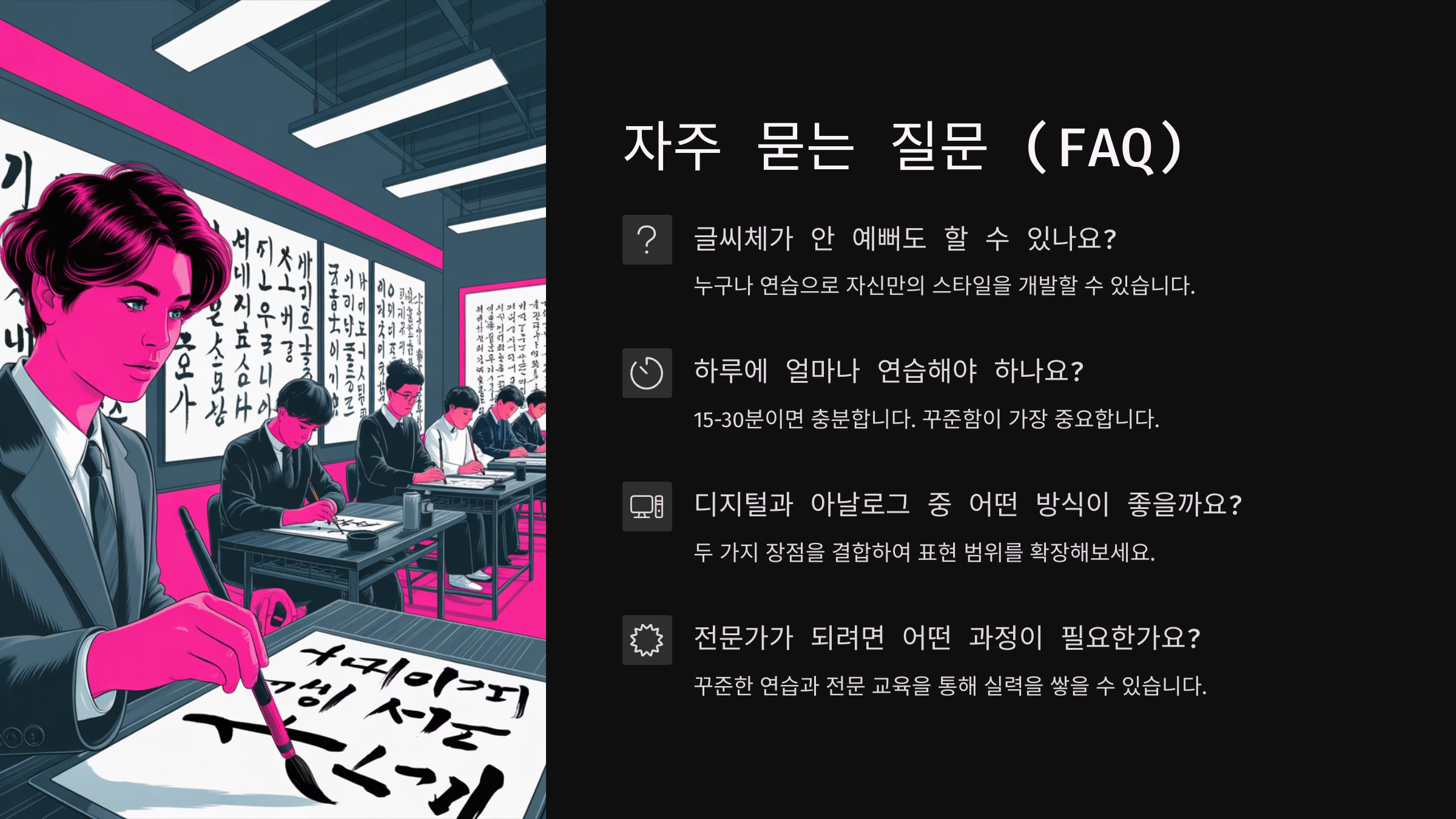
요즘 캘리그라피, 특히 감성글씨가 인기 많죠? 손글씨 특유의 따뜻함과 감성이 담긴 글자 하나가 보는 사람 마음을 울리기도 해요. 이 감성글씨는 단순한 디자인이 아니라, 글씨에 담긴 감정과 메시지를 전하는 예술 형태랍니다.
디지털 시대임에도 불구하고 사람들은 여전히 손으로 쓴 글씨에서 위로와 여유를 느끼고 있어요. 특히 SNS에서는 감성 캘리그라피 글귀가 수많은 공감을 얻으며 공유되고 있죠. '나도 저렇게 써보고 싶다'는 생각, 한 번쯤 해본 적 있지 않으신가요?
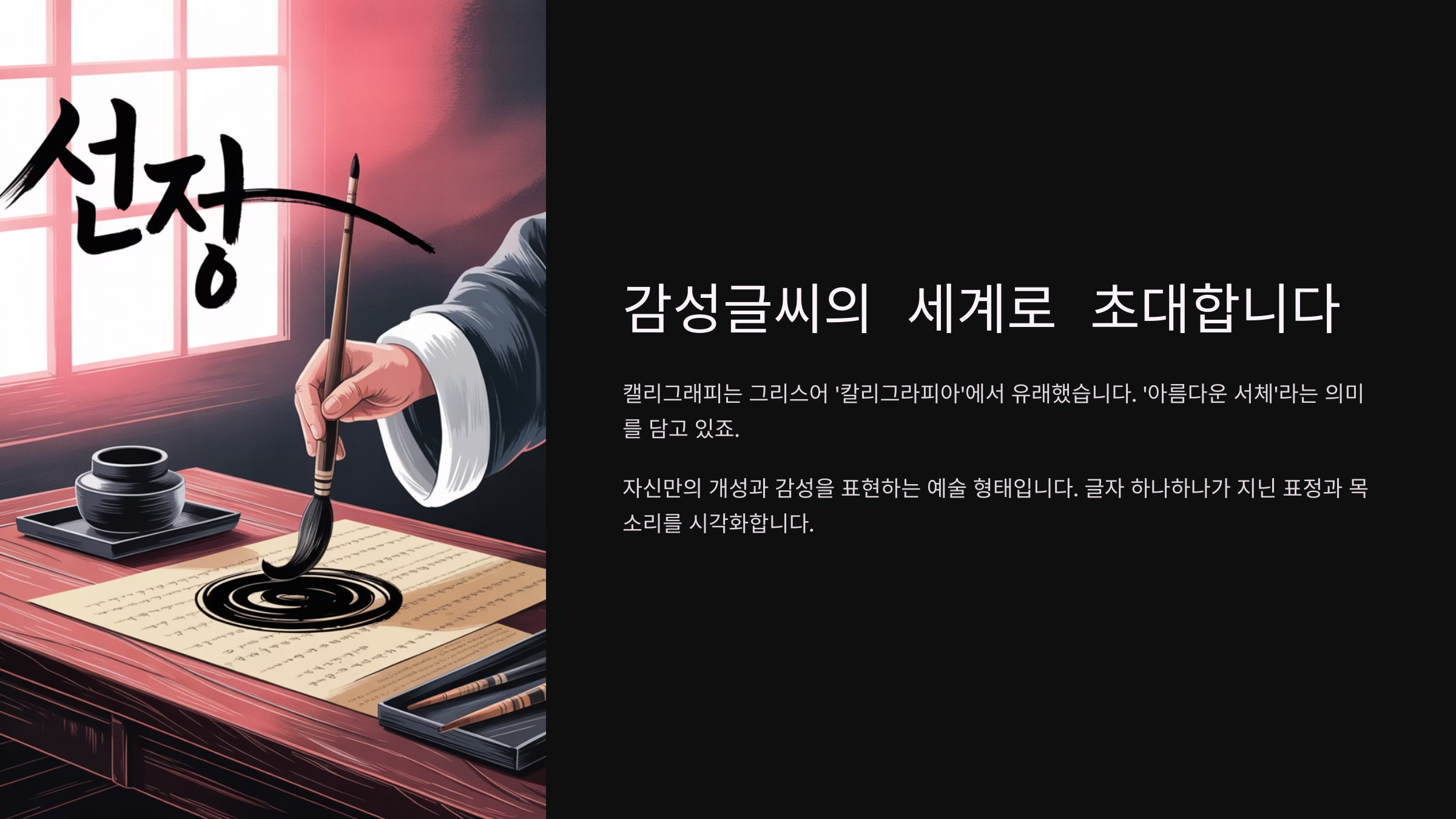
이제부터 그 질문에 대한 답을 찾아가볼게요. '나도 작가가 될 수 있을까?'에 대해 진심 어린 가이드와 함께 시작해보자고요 😊
✒ 감성글씨의 탄생과 유래
감성글씨의 탄생과 유래
감성글씨는 단순한 손글씨를 넘어서 하나의 감정 표현 수단으로 자리 잡았어요. 이 표현은 2000년대 후반부터 본격적으로 사용되기 시작했고, 특히 한국에서는 ‘글씨로 마음을 전하다’라는 문화와 연결되면서 큰 인기를 얻었죠. 붓펜과 만년필, 심지어 수성펜까지 활용해 개성 있는 글자체를 만들어내는 것이 특징이에요.글씨 하나하나에 따뜻한 감성과 이야기를 담는 이 작업은, 디지털 글꼴로는 느낄 수 없는 정서를 전달해요. 옛날 서예가 한문을 통해 뜻을 표현했다면, 오늘날 감성글씨는 일상 언어와 문장을 통해 감정까지 전하는 거죠.
예전에는 정형화된 글씨가 '예쁜 글씨'로 여겨졌지만, 요즘은 비뚤거나 흐트러져 있어도 괜찮아요. 오히려 그 안에서 더 인간적인 매력을 느낄 수 있으니까요. 손글씨를 통해 나만의 스타일을 표현하는 시대가 온 거예요.
이 감성 캘리그라피는 시인, 작가뿐 아니라 일반 사람들도 자신의 이야기를 담는 데 활용해요. 축하카드나 명함, 책갈피, 포스터 등에도 자주 쓰이고 있고, 온라인 클래스나 유튜브를 통해 배울 수 있는 콘텐츠도 무척 많아졌죠.
🖋 캘리그라피 장르별 특징 비교
장르 도구 특징 활용 예시 전통 서예 붓, 먹 획 중심, 격식 있음 한자, 명언 쓰기 현대 캘리그라피 붓펜, 사인펜 자유로운 선, 감성 강조 SNS글귀, 상품 포장 디지털 캘리 아이패드, 스타일러스펜 레이어 작업, 수정 용이 굿즈, 웹 포스터 캘리그라피는 이렇게 다양한 장르로 나뉘어요. 도구나 스타일에 따라 분위기도 달라지고, 쓰임새도 확연히 달라지는 게 참 흥미로워요. 내가 생각했을 때 감성글씨는 나만의 감정을 솔직하게 담아내는 하나의 언어라고 느껴져요 🧡
💗 왜 감성글씨에 끌릴까?
왜 감성글씨에 끌릴까? 사람들은 왜 디지털 폰트보다 감성글씨에 더 감동할까요? 이유는 바로 '사람의 손'이 느껴지기 때문이에요. 캘리그라피는 글자의 모양을 넘어 그 속에 담긴 감정과 분위기를 함께 전달해줘요. 그래서 그 한 줄이 누군가에겐 위로가 되고, 하루를 웃게 만들어주는 힘을 지니는 거죠.
특히 현대인들은 하루 종일 스마트폰이나 컴퓨터 앞에 앉아 있는 경우가 많잖아요. 그래서 종이에 손으로 쓰는 행위 자체가 힐링처럼 느껴지는 거예요. 글씨 하나에 감정과 정성이 담긴다는 걸 알게 되면, 그 매력에서 빠져나오기 힘들어요.
감성글씨는 '꾸며야 예쁘다'는 강박에서 벗어나 있어요. 삐뚤빼뚤해도 좋고, 조금 서툴러도 돼요. 중요한 건 그 글자에 담긴 마음이죠. 그 점이 많은 사람에게 편안함을 주고, 자신도 해보고 싶다는 욕구를 자극해요.
실제로 SNS를 보면 “오늘 하루 수고했어”, “있는 그대로도 괜찮아” 같은 짧은 문장이 손글씨로 적혀 있을 때 훨씬 더 와닿는 걸 볼 수 있어요. 폰트로 쓴 말보다 손글씨 한 줄이 위로가 되는 이유, 이제 아시겠죠? 😊
💞 감성글귀 반응 비교
문장 유형 글자 형태 느껴지는 감정 공감도 "오늘도 수고했어요" 폰트 텍스트 무난, 일상적 ★★☆☆☆ "오늘도 수고했어요" 손글씨 캘리 따뜻함, 위로 ★★★★★ 위의 비교처럼 같은 문장이라도 감성글씨로 표현되면 그 감동은 두 배 이상 커져요. 글씨체 하나로 누군가의 하루를 따뜻하게 만들어줄 수 있다니, 참 멋지지 않나요? 🎨
🖌 캘리그라피, 어떻게 시작할까?
캘리그라피, 어떻게 시작할까
감성글씨, 캘리그라피를 시작하고 싶다면 먼저 마음가짐부터 달라져야 해요. 완벽하게 써야 한다는 부담은 잠시 접어두고, ‘내 감정을 글씨로 표현한다’는 생각으로 시작해보세요. 처음에는 어색하고 마음에 들지 않아도 괜찮아요. 꾸준히 쓰다 보면 글씨에 나만의 분위기가 자연스럽게 묻어나거든요.가장 먼저 해야 할 일은 다양한 캘리그라피 스타일을 관찰하는 거예요. SNS나 유튜브에서 ‘캘리그라피’, ‘감성글씨’ 키워드로 검색하면 수많은 예시를 볼 수 있어요. 이 중에서 마음에 드는 스타일을 골라 따라 써보는 것이 큰 도움이 된답니다.
처음엔 연습 노트 하나 준비하고, 가장 익숙한 펜이나 붓펜으로 연습을 시작해도 좋아요. 유명 작가들의 글씨체를 따라 써보는 것도 추천하고요. 손의 움직임, 획의 방향, 굵기 변화 등을 익히는 데 도움이 되니까요.
글씨를 쓴 후에는 꼭 사진을 찍어서 저장해보세요. 비교하면서 내 글씨가 어떻게 달라졌는지 보는 것도 재미있고, 꾸준히 연습하고 있다는 성취감도 느낄 수 있거든요. 나만의 발전 과정을 보는 건 정말 뿌듯해요 ✨
📘 캘리그라피 입문 순서 가이드
단계 활동 목표 1단계 좋아하는 글귀 찾아보기 자극과 영감 받기 2단계 글씨체 따라 써보기 기본 선 연습 3단계 문장 단위 연습 감성 전달 익히기 4단계 자신만의 스타일 찾기 작가로서의 개성 개발 이렇게 단계를 나눠 차근차근 시도해 보면, 감성글씨도 결코 어려운 것이 아니라는 걸 느끼게 될 거예요. 감정과 손의 감각이 익숙해지면, 글씨에 자연스럽게 ‘나’가 녹아들게 되니까요 💫
🎨 필요한 도구와 재료 정리
필요한 도구와 재료 정리
감성글씨를 시작하는 데 꼭 고급 장비가 필요한 건 아니에요! 일상 속에서 쉽게 구할 수 있는 도구로도 충분히 멋진 작품을 만들 수 있어요. 특히 처음 시작할 땐 '나에게 맞는 도구가 무엇인지'를 찾는 것이 중요하답니다.우선 기본 중의 기본은 펜이에요. 붓펜, 사인펜, 만년필, 연필까지도 모두 감성글씨에 사용 가능해요. 붓펜은 획의 굵기 조절이 용이해서 감정을 표현하기 좋아요. 사인펜은 깔끔하고 귀여운 스타일을 연출하기에 적합하고요.
종이는 너무 매끄럽지 않은 종류를 추천해요. 일반 복사용지보다 조금 더 두껍고 부드러운 재질의 종이가 붓펜 잉크를 잘 받아줘요. 마트나 문구점에서도 쉽게 구할 수 있는 '스케치북용 도화지'도 괜찮은 선택이에요.
그 외에 필요한 건 연습장, 연필, 지우개, 색연필 정도예요. 다양한 색을 사용하면 분위기가 훨씬 따뜻해지거든요. 그리고 잊지 마세요! 스마트폰은 작업물을 기록하는 중요한 도구예요. 사진을 찍어서 SNS에 공유하거나 발전 과정을 남기기에도 좋답니다 📸
🧰 캘리그라피 추천 도구 리스트
도구명 특징 사용 용도 추천 대상 모나미 붓펜 획 굵기 자유조절 가능 감성 캘리그라피 초보자 파버카스텔 색연필 색감이 풍부하고 부드러움 글씨 데코레이션 감성 스타일 좋아하는 분 무지노트 A5 간편한 연습용 노트 글귀 연습, 낙서 모든 입문자 아이패드 + 프로크리에이트 레이어 편집, 브러시 다양 디지털 감성글씨 제작 디자인 작업 원하는 분 너무 많은 도구보다, 하나씩 써보고 나에게 잘 맞는 걸 찾는 게 더 중요해요. 때로는 펜 하나만으로도 깊은 감정을 표현할 수 있답니다. 손에 익고, 감정이 따라올 때 그 글씨는 진짜 ‘내 글씨’가 돼요 🖋
📖 매일 쓰는 연습법 공유
매일 쓰는 연습법 공유 감성글씨는 하루아침에 뚝딱 완성되는 게 아니에요. 하지만 매일 10분이라도 꾸준히 연습한다면 분명히 달라지는 걸 느낄 수 있어요. 짧고 간단한 글귀 하나씩 써보는 것부터 시작해보는 게 좋아요. 너무 긴 문장을 고르기보단, '오늘도 수고했어' 같은 짧고 마음 따뜻해지는 문장이 더 좋아요.
연습을 할 땐 그날의 기분을 담아보세요. 기분이 가라앉은 날은 느릿하고 부드러운 획으로, 활기찬 날은 힘 있게 써보는 거예요. 글씨에도 감정이 담기기 때문에 그 날의 마음이 그대로 전달되거든요. 매일의 글씨를 모아보면 내 기분 노트가 되기도 해요 💬
글씨 연습 전에는 손을 가볍게 풀어주는 것도 좋아요. 손목 스트레칭을 1분만 해줘도 붓펜 움직임이 훨씬 유연해지고, 감정도 글씨에 더 잘 담겨요. 그리고 글씨체 연습은 ‘선 따라 쓰기’부터 시작해서 점점 자유로운 문장으로 확장해보면 돼요.
그리고 연습할 때는 꼭 날짜를 적어두는 걸 추천해요. 나중에 보면 '이만큼 발전했구나' 하고 스스로 감동하게 된답니다. 이건 꼭 남을 위해서가 아니라 나를 위해 남기는 기록이기도 해요 📅
🗓 일주일 캘리그라피 연습 루틴
요일 연습 내용 시간 포인트 월요일 선 따라 그리기 10분 손에 감 익히기 화요일 자음/모음 조합 쓰기 10분 기초 글자 형태 익히기 수요일 짧은 단어 써보기 10분 균형 잡힌 구조 목요일 감성 글귀 필사 10분 감정 담기 연습 금요일 자유 문장 작성 10분 개성 표현 이 루틴대로 연습하다 보면 어느새 글씨에 감정이 녹아들고, 표현하는 재미에 푹 빠지게 될 거예요. 연습은 힘든 게 아니라, 매일 나와 대화하는 시간이라 생각하면 더 즐거워질 거예요 🧡
🌟 감성글씨 활용법과 작품화
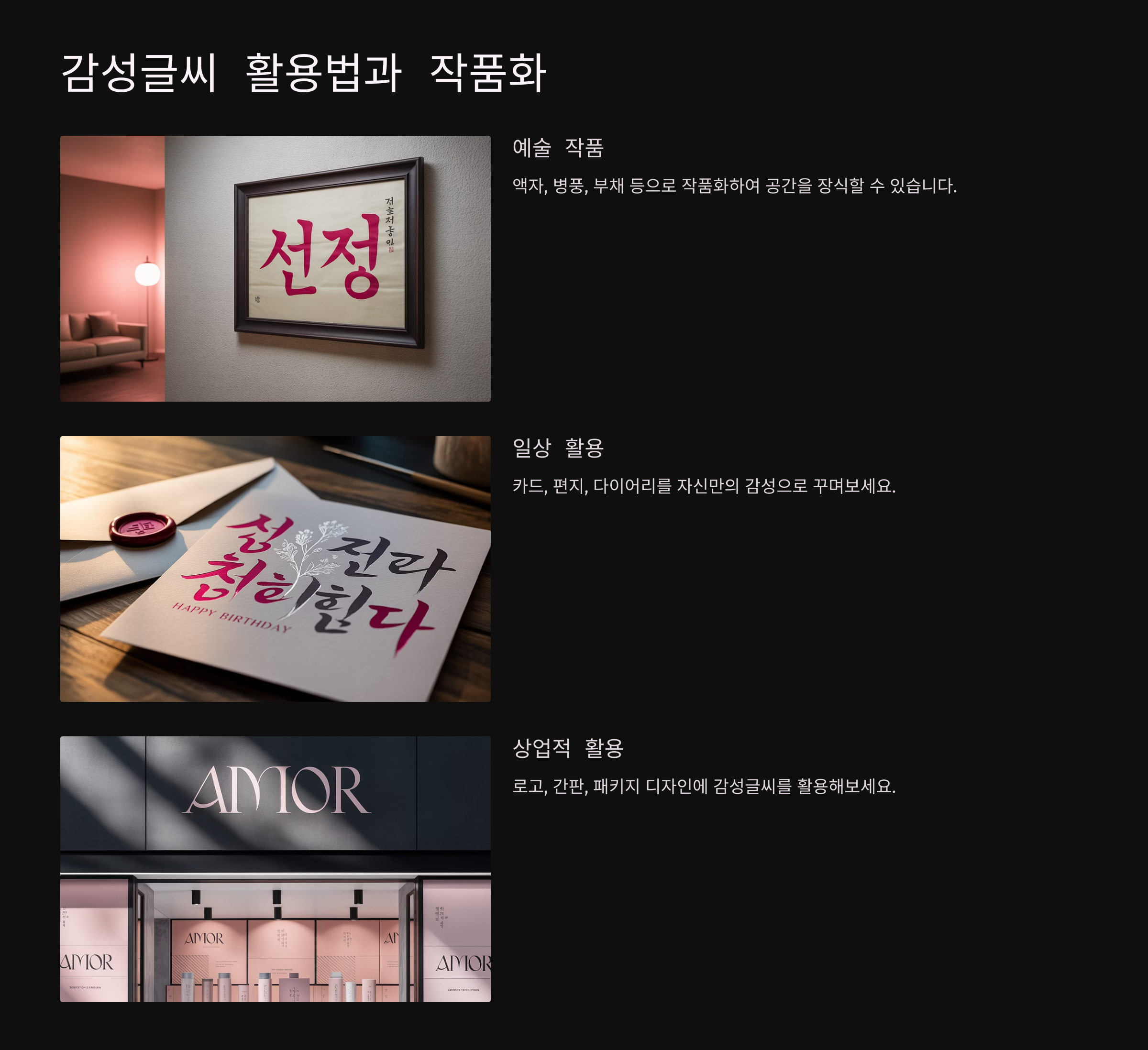
감성글씨 활용법과 작품화
연습한 감성글씨를 어디에 쓰면 좋을까요? 단순한 글쓰기에서 벗어나 실생활에서 활용하면 그 매력이 배가돼요. 무엇보다 ‘내 글씨가 누군가에게 의미가 될 수 있다’는 걸 느끼면, 더 큰 보람과 성취감을 맛볼 수 있답니다 💌가장 많이 활용되는 분야는 ‘손글씨 엽서’나 ‘캘리그라피 카드’예요. 누군가에게 따뜻한 말을 전할 때, 예쁜 배경에 감성글씨로 적힌 한 문장은 전하는 마음을 더욱 깊고 진하게 만들어줘요. 기념일 카드, 생일 메시지, 위로의 글귀 등으로도 정말 인기가 많죠.
요즘은 SNS, 특히 인스타그램에서도 감성글씨 콘텐츠가 폭발적인 반응을 얻고 있어요. 짧고 강렬한 한 문장, 감정이 묻어나는 한 단어를 예쁜 배경 위에 올리는 것만으로도 많은 사람들의 공감을 살 수 있답니다. 해시태그만 잘 붙이면 자연스럽게 많은 사람들과 연결될 수 있어요.
Q4. 하루에 얼마나 연습해야 효과가 있나요?
A4. 하루 10분 정도면 충분해요. 중요한 건 매일 꾸준히 하는 거예요. 짧더라도 매일 쓰는 게 실력을 키워주는 비결이에요!
Q5. 글귀는 어디서 찾으면 좋을까요?
A5. 책, 영화 대사, 노래 가사, 명언집, 인스타 피드 등에서 감동적이고 공감 가는 문장을 찾아보세요. 나만의 느낌으로 다시 써보면 훨씬 좋아요.
Q6. 감성글씨로 돈을 벌 수 있을까요?
A6. 네, 가능해요! 굿즈 제작, SNS 콘텐츠 제작, 주문제작 엽서 판매 등 다양한 수익화 방법이 있어요. 자신만의 스타일을 확립하면 수익 창출도 가능하답니다 💰
Q7. 글씨에 감정을 담는 팁이 있을까요?
A7. 글씨를 쓸 때 그 문장을 읽고 마음속으로 한 번 더 느껴보세요. 그 감정 그대로 획을 그리면, 자연스럽게 감성도 따라오게 돼요 🖌
Q8. 감성글씨로 작가가 되려면 어떤 준비가 필요할까요?
A8. 나만의 글씨체와 메시지를 꾸준히 만들어가며 SNS나 블로그에 포트폴리오를 쌓는 게 좋아요. 클래스 운영이나 전시 참여도 큰 도움이 돼요.